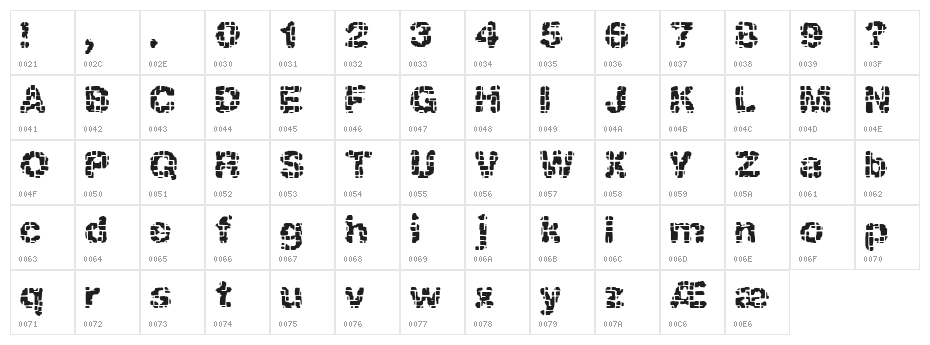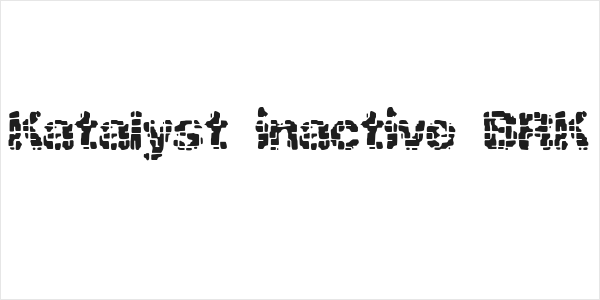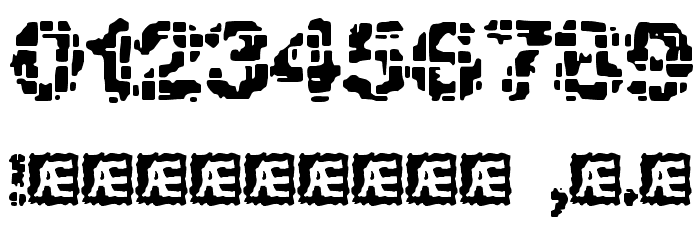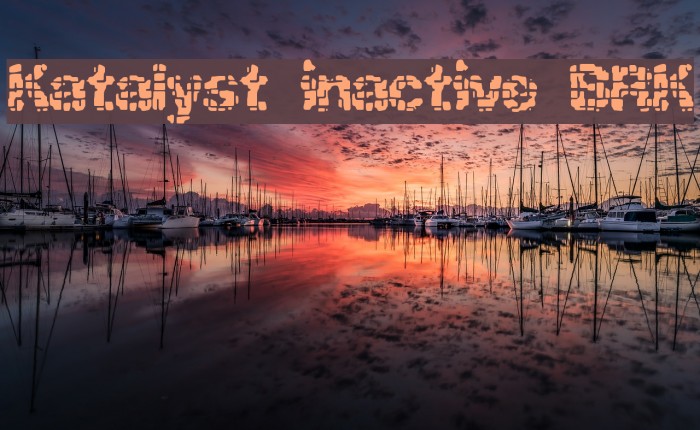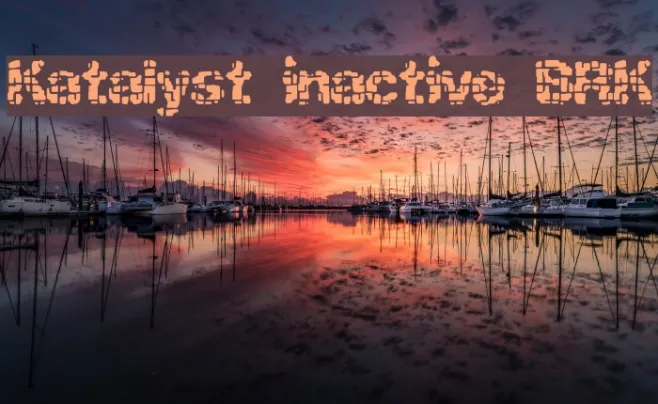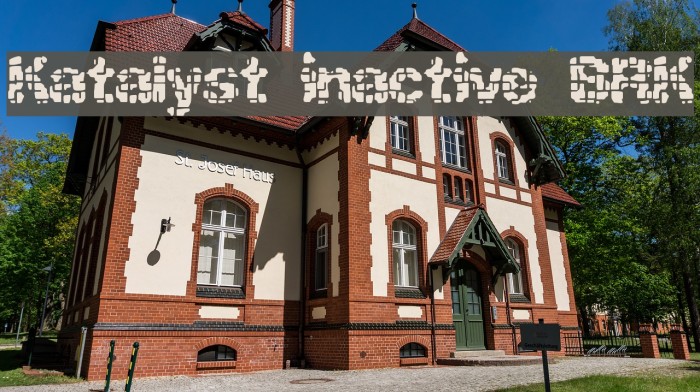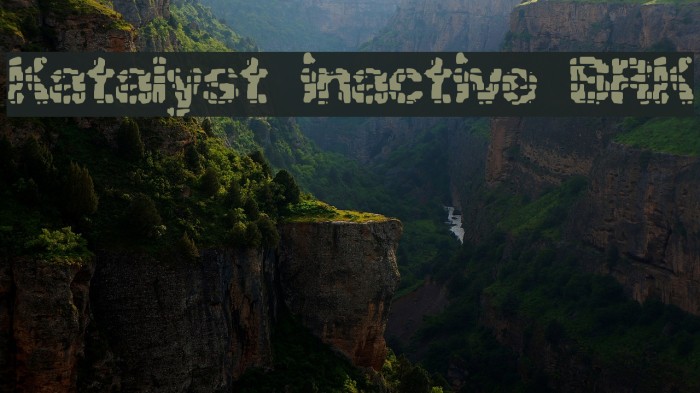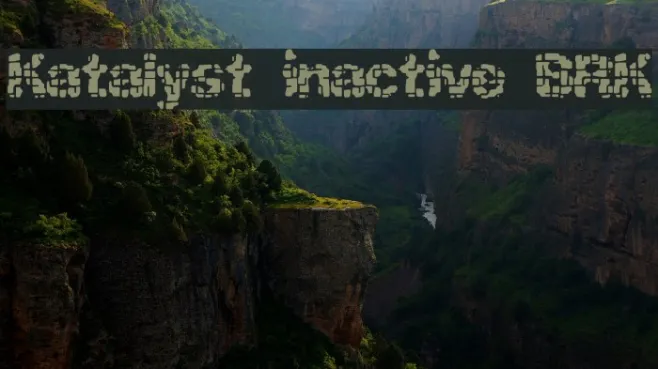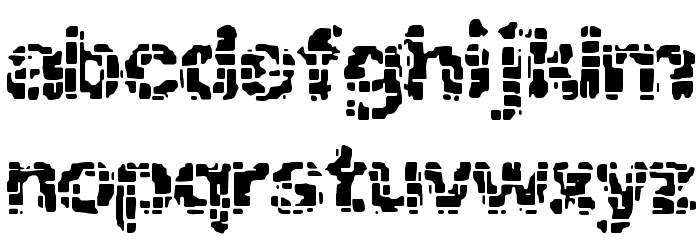
Katalyst inactive BRK Font
| Vorgeschlagene Projekte | Ideal for tech-themed designs, video game graphics, digital art projects, and modern branding. |